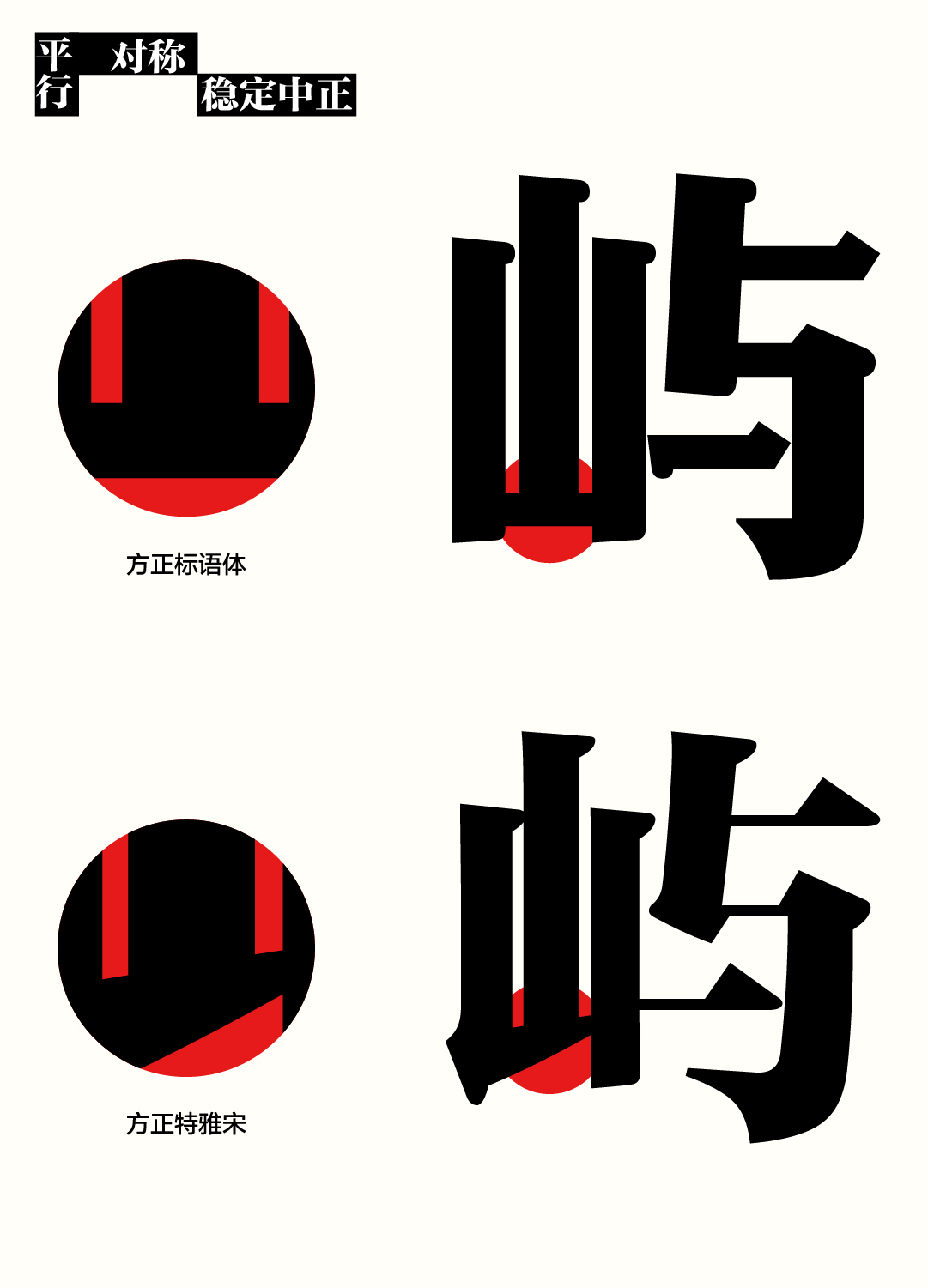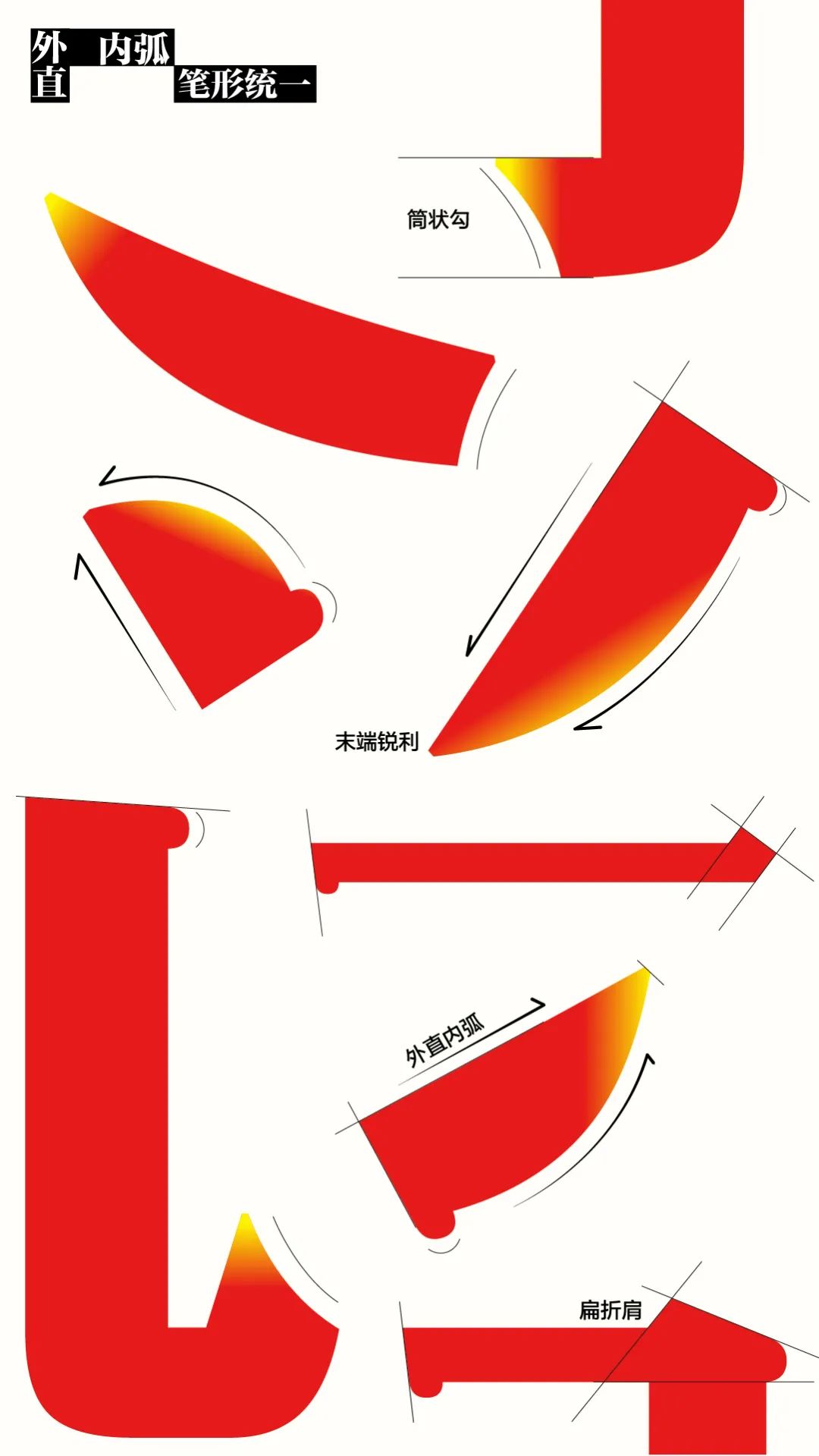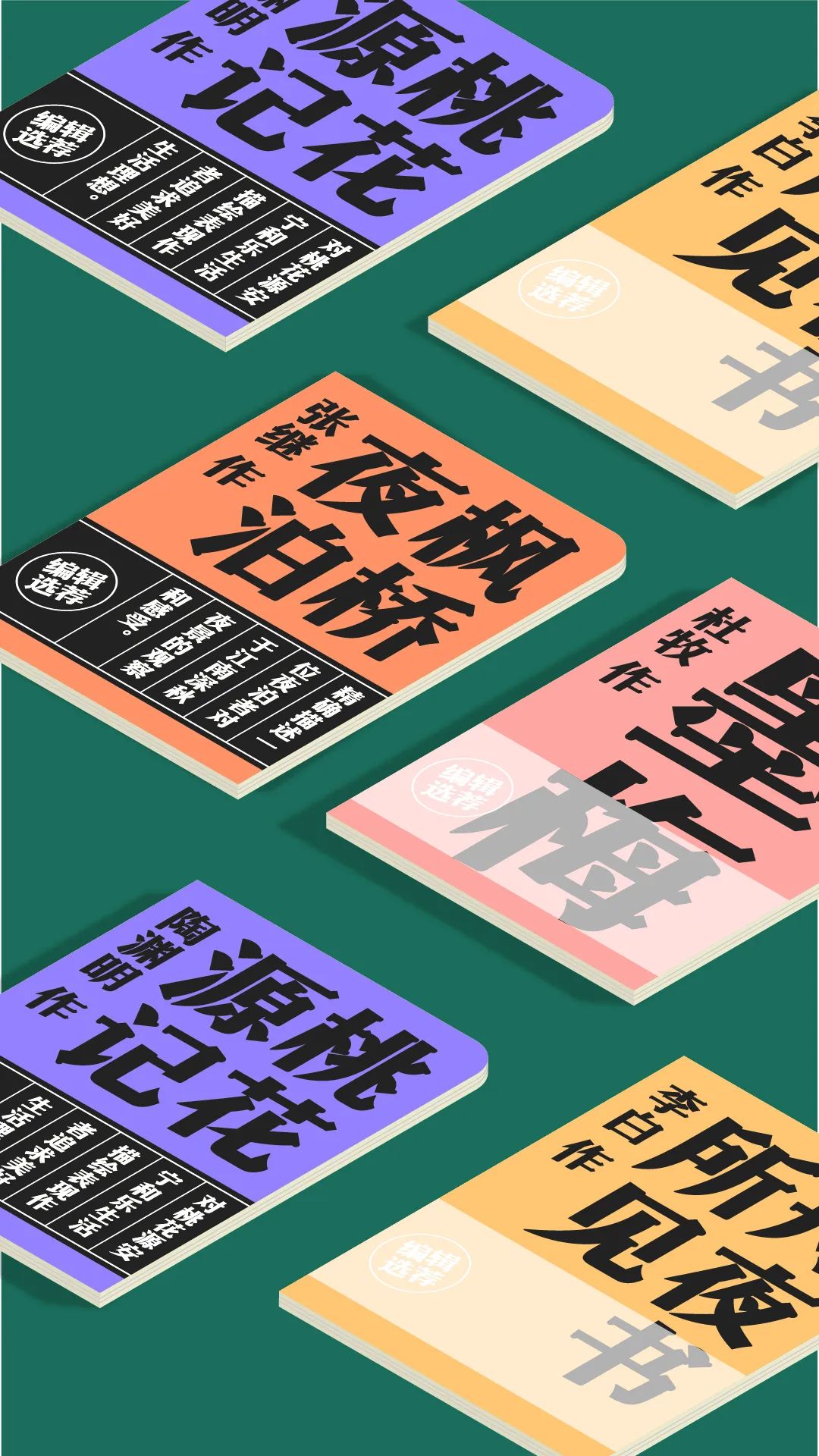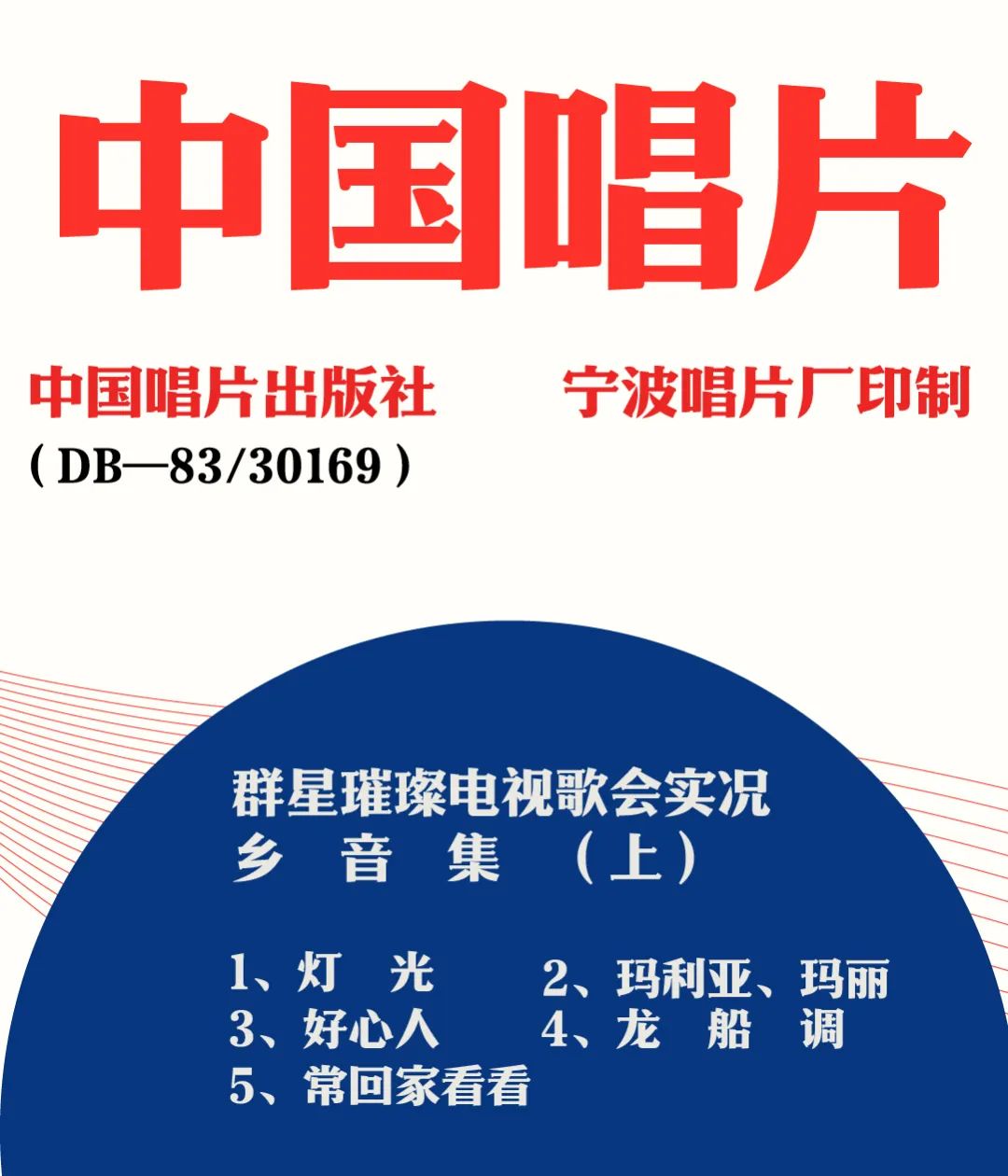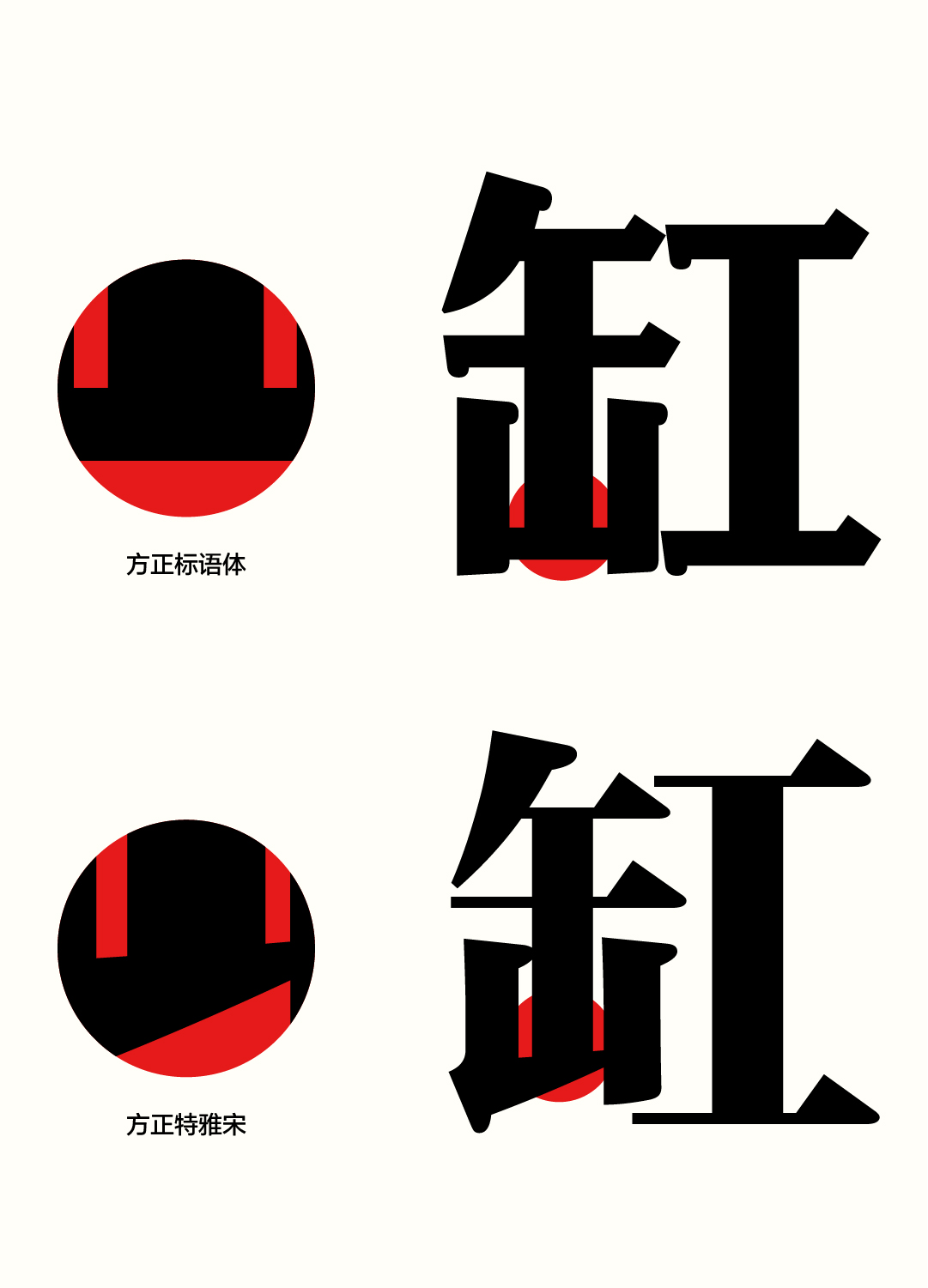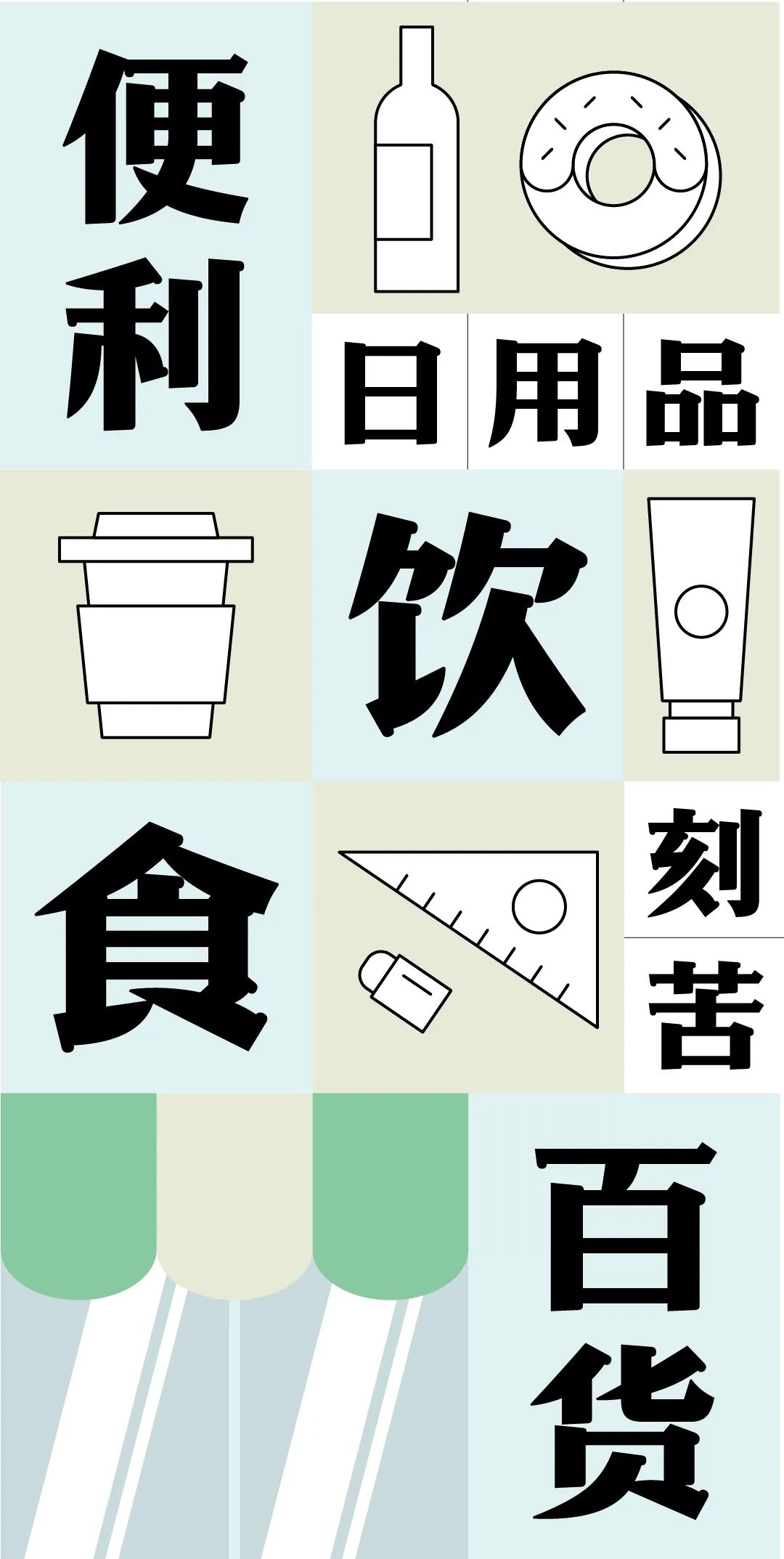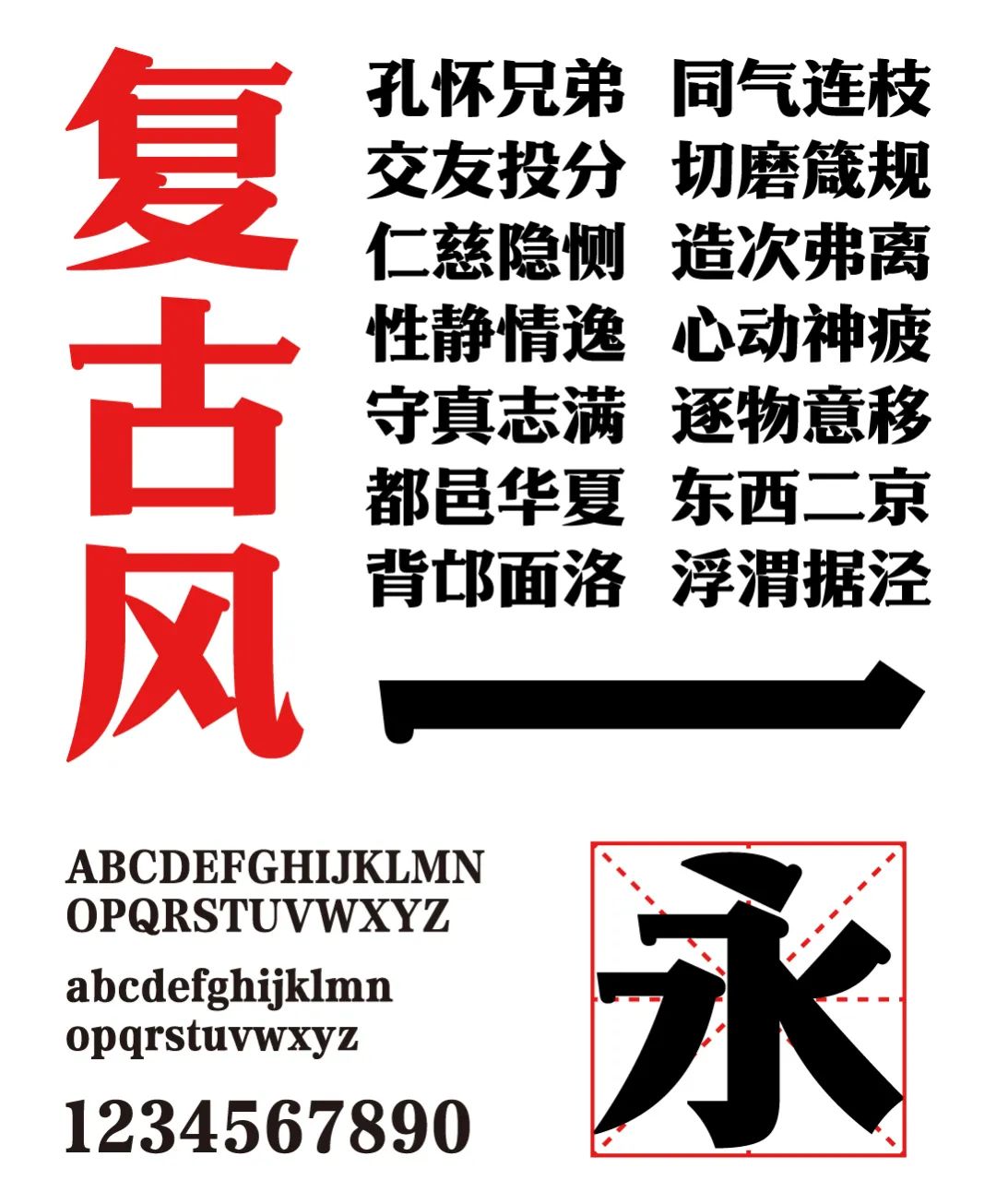
方正标语体
方正标语体,这款字体结构工整、笔画清晰,兼顾美观与易读性,适用于标题、正文、海报、包装、LOGO 等多种场景。字形优雅稳定,风格百搭耐看,适配日常排版与创意设计,让文字呈现更舒适、更具质感。方正标语体一笔一画,皆是细节,以均衡的比例、流畅的线条打造舒适视觉体验,字形端正大气,风格简约现代。无论是商业设计、品牌宣传还是日常排版,都能轻松驾驭,让文字更有格调与力量。方正标语体字体下载。
方正标语体起源于方正字库受委托为2019年天安门广场庆祝新中国成立70周年大型活动、2021年庆祝中国共产党成立100周年大会打造的定制字体,字体参考了北京天安门城楼两侧横幅标语的老式宋体字形,融合设计师个人理解,改良完善并设计扩展为一套字库,继承传统复古风并对旧字形和结构提纯改良为符合新时代的字体。天安门字形历经数十载风雨洗礼,将其演化为字库,既是对历史和文化的见证,又是对传统美术字体典范的传承,使其在新时代焕发新的神采。
标语体字形采用宋体与黑体融合,既有宋体的衬线与书写性,又具黑体的粗重醒目。采用劲挺的老美术字笔形,有手写的力量感,且结构端正,具历史感与仪式感。字面饱满、中宫开阔,厚重劲挺且庄严醒目。字形宽博、字面略扁,可有效增强阅读流畅性与舒适度。适合标语类文字及书报刊、包装、广告、屏幕等大、小标题用字,小段落正文亦可使用。
标语口号的视觉化,
是一种十分具有中国特色的现代文化现象,
作为标语口号的视觉载体和宣传武器,
标语字体的设计具有特别的价值和意义。
方正标语体,
酌取天安门城楼标语设计灵感,
重现时代视觉记忆,
值此盛世华诞隆重发布。
在新中国成立初期,标语口号作为一种重要的意识形态宣传方式广为流行,标语字体在视觉上需要呈现出「壮观」「醒目」「突出」的特点,以此鼓舞士气、唤醒民众,宣誓出革命力量的坚定意志和摧枯拉朽的气势。这其中最重要,也最经典的,当属天安门城楼上毛主席像两侧的巨幅标语——「中华人民共和国万岁」和「世界人民大团结万岁」。
其实,最初毛主席画像两侧最初书写的巨幅标语是「中华人民共和国万岁」和「中央人民政府万岁」。同时,由于当时国徽方案尚未确定,临时决定在悬挂国徽的位置上悬挂大典的标题字——「中华人民共和国中央人民政府成立典礼」。这些标语文字,均交由当时担任中国人民政治协商会议筹备委员会总务处办公室主任兼会场布置科科长钟灵,来负责书写和设计。
在开国大典之前,钟灵接到了书写天安门城楼标语这一项艰巨而又光荣的任务,他干劲十足,全心投入在巨幅标语的创作中,但在这个过程中也遇到了不少困难。
钟灵首次书写天安门城楼标语
例如:天安门城楼红墙绵长,标语上的每个字都足有两米见方,钟灵之前从未书写过那么大的美术字,于是他认真丈量天安门城楼的长度,精心计算每个字的大小,再用尺子和铅笔先创作出标语的字形,之后又在布上剪出这些大字,并指导木工按照1:100的比例锯好木板、钉成字盒,外面装上一层毛玻璃,里面再安上灯泡,这样标语的字盒就像是广告灯箱,通电之后即便是夜晚从远处观看,也能看清大标语的内容。
此外,当时书写的标语「中华人民共和国万岁」和「中央人民政府万岁」的字数不一样多,如何在视觉上让两侧的标语对称是另外一大难点。钟灵在实际测量中发现,天安门的九间门楼实际上宽窄不等,但在人们的视觉中看起来是左右对称,于是他决定利用视觉错觉原理,来规划标语口号每个字之间的间距。
在字体风格上,钟灵选择了庄重醒目、大方规整的「大宋体」,也就是笔画和字体间架结构上带有楷书风格的宋体字,宽博严谨、落落大方;同时,由于建国初期还没有通行简体字,所以这些大标语最初都是用繁体字书写的。1949年9月底,两条巨幅标语赫然悬挂于天安门城楼上,见证新中国的成立。
开国大典上天安门城楼前的欢庆队伍
开国大典之后,按照周总理的指示,天安门两侧的标语被保留下来,东边位置的「中央人民政府万岁」被改成「世界人民大团结万岁」,这样不但使两边的标语字数相同,还可以避免之前因字数不等,在设计书写时造成的字间距不统一的问题,同时也兼具了爱国主义和国际主义精神。
1956年,国务院公布汉字简化方案,简体字正式取代繁体字字形。1964年国际劳动节前夕,天安门城墙上标语中的「华」「国」「万」「岁」「世」「团」六个字由繁体字改为简体字,同时也对字体的风格进行了调整,从比较圆润敦厚的大宋体改成了一种更加直率硬朗的宋黑体,在某些细枝末节的地方还保留着一点大宋体的味道。
天安门城楼标语改为简体字并沿用至今
天安门城墙上的大标语视觉风格硬朗,成为毛主席时代全国各地书写大标语和宋体字的典范。历经数十年风雨洗礼,其地位之显要、尺寸之巨大,保存时间之长久,被认为是宋体美术字的典范。
方正标语体起源于方正字库受委托为2019年天安门广场庆祝新中国成立70周年大型活动、2021年庆祝中国共产党成立100周年大会打造的定制字体。设计师酌取天安门城楼两侧标语口号字体的「大宋体」字形特征与革命精神,并融合设计师个人理解和新时代字体审美,继承宋体美术字的传统复古风格,改良完善并设计扩展为一套完整的字库字体,使天安门城楼标语代表的时代革命精神,在新时代焕发新的光彩。
方正标语体采用宋黑体融合的设计风格,既有宋体的衬线装饰与书写性,又具有粗黑体粗重醒目的视觉特点,字形宽博,字面饱满且略为宽扁,中宫开阔,具有厚重劲挺的力量感,整体视觉风格直率硬朗、庄严醒目。
在笔形设计上,方正标语体采用劲挺的老美术字笔形,保留宋体的笔画特征,横细竖粗,有装饰字脚,棱角分明;不同笔画的笔锋相同、大小一致,笔画最粗处宽度一致,强调规律性与统一性。
方正标语体笔画轮廓线外侧绷直,内侧曲线饱满,撇画的收笔和捺画的起笔尖锐利落,长撇转折处干脆直接,笔画虽厚重但不粗笨,具有强烈的视觉韧性。
考虑到视觉上的稳定性,部分偏旁如“山”“缶”等的竖折笔画没有采用宋体通常的提笔,笔画平行对称,稳定中正。
同时为了强化手写的感觉,捺头单起笔进行了分离设计,巧妙地避让笔锋,增强字体的书写性。
方正标语体来自于对历史的见证,以及对传统美术字体典范的传承,其鲜明的字体特征有效增强了阅读流畅性与舒适度。
字体非常适用于视觉冲击力强的标题短语类文字排版,书籍、报刊、包装、广告、屏幕等大小标题,以及小段落正文均可适用。
2019年10月1日,方正字库受委托为在天安门广场举行的「庆祝新中国成立70周年大会」活动提供视觉背景支持,方正标语体首次亮相,圆满完成任务。
「庆祝新中国成立70周年大会」活动现场
2021年7月1日,在天安门广场举行的「庆祝中国共产党成立100周年大会」活动现场,天安门广场的两块大屏幕上循环播放着应用方正标语体制作的庆祝标语视频,及建党百年庆祝活动标识的视频,由方正字库打造的方正标语体呈现庄重大方的大国气势,连续16天持续服务保障活动前期综合演练及大会当日活动现场展示效果。
「庆祝中国共产党成立100周年大会」活动中使用方正标语体排版的视频展示